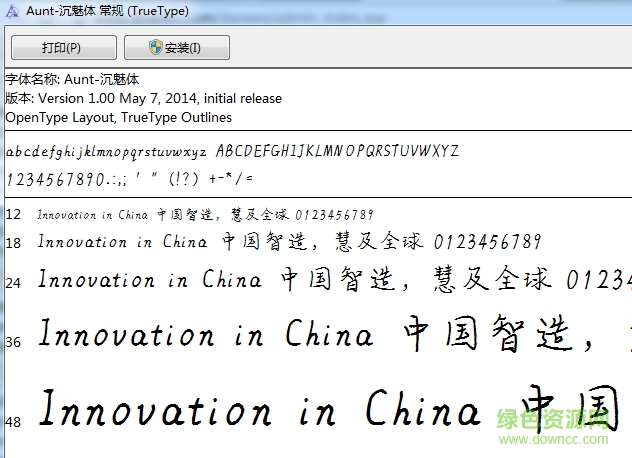
魅力小寶體字體是一款超好用的個(gè)性英文字體,字體擁有獨(dú)特的線條組成,給予用戶(hù)不同的感官,有喜歡這款字體的朋友可以來(lái)綠色資源網(wǎng)免費(fèi)下載使用!
魅力小寶體字體是一款極具個(gè)性的字體,該字體十分飄逸,彰顯了自己的個(gè)性,有喜歡的朋友可以來(lái)綠色資源網(wǎng)下載使用!